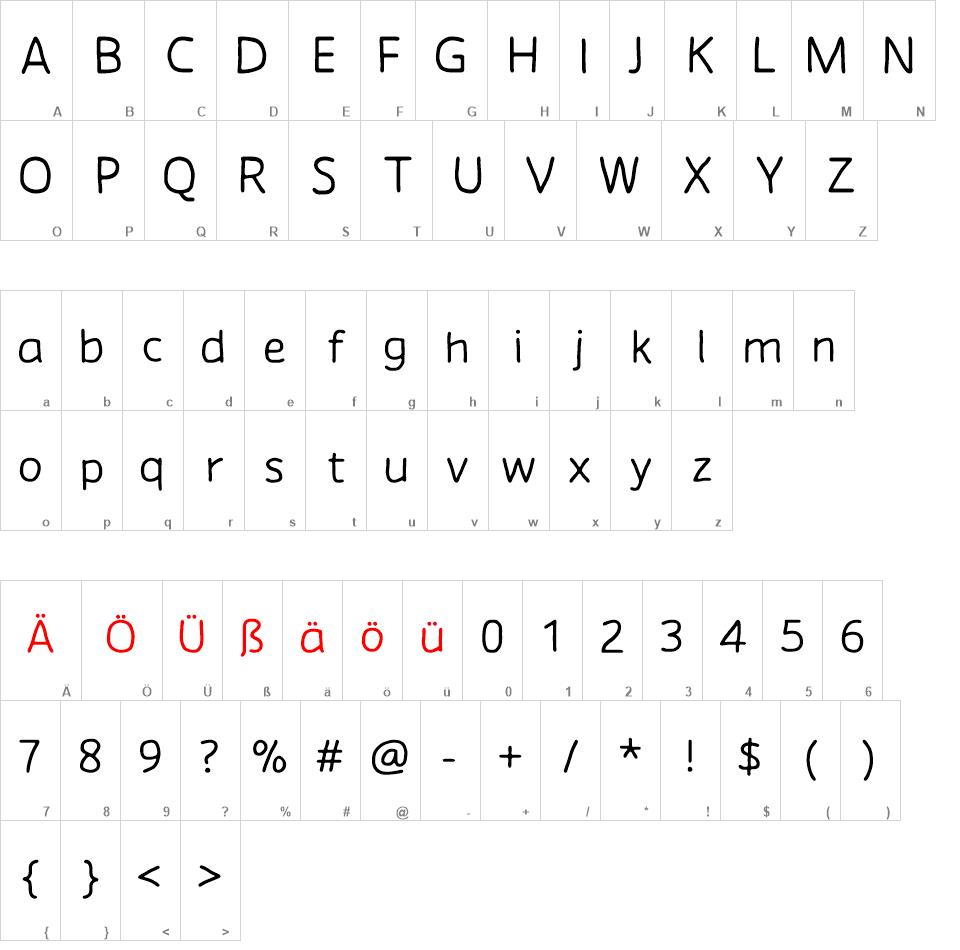
Chirota
Chirota font
Chirota
Chirota ist eine handgeschriebene Schrift von Situjuh Nazara. Seine klaren Linien mit einem wackeligen Look & Feel macht Chirota besonders einzigartig. Durch die Konsistenz der einzelnen Zeichen, die der Sans Serif nahe kommen, und durch das gute Maß an Metriken und Kerning ist diese Schriftart sehr leicht zu lesen.